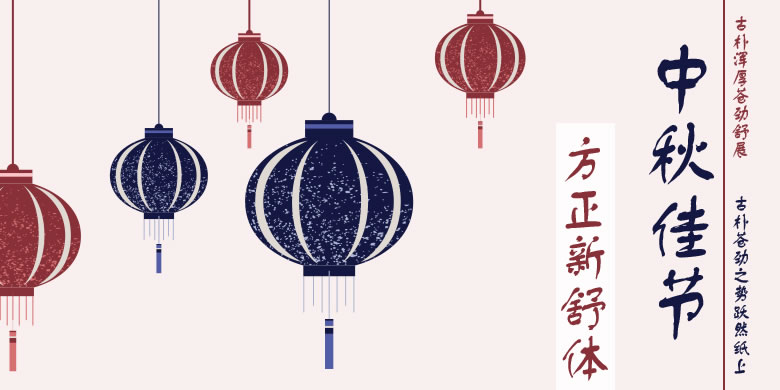
方正新舒体
字体品牌: 方正字库 设计师:孙志皓 字体分类:行书、创意书写、创意字体 字体属性:精品字 字符集:大陆简体(GB2312-80)、简繁扩展(GBK) 发布时间: 2000
方正新舒体由书法家孙志皓先生创作。这款字体是在原方正舒体的基础上重新构思和书写的。和方正舒体相比,方正新舒体加粗了笔画,在结构和笔意的处理上也表现得更加成熟和自如。其风格浑厚深沉,适用于文化类的宣传设计,以及商业类品牌的广告和产品包装设计。